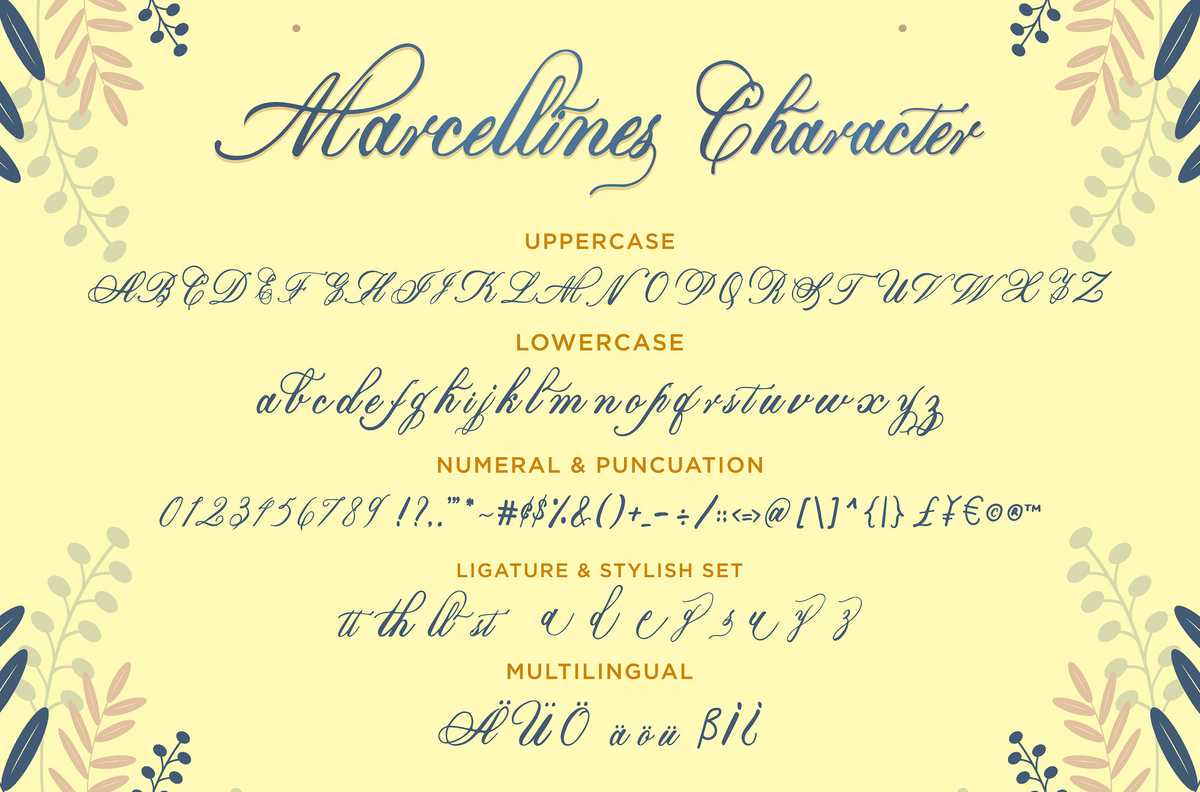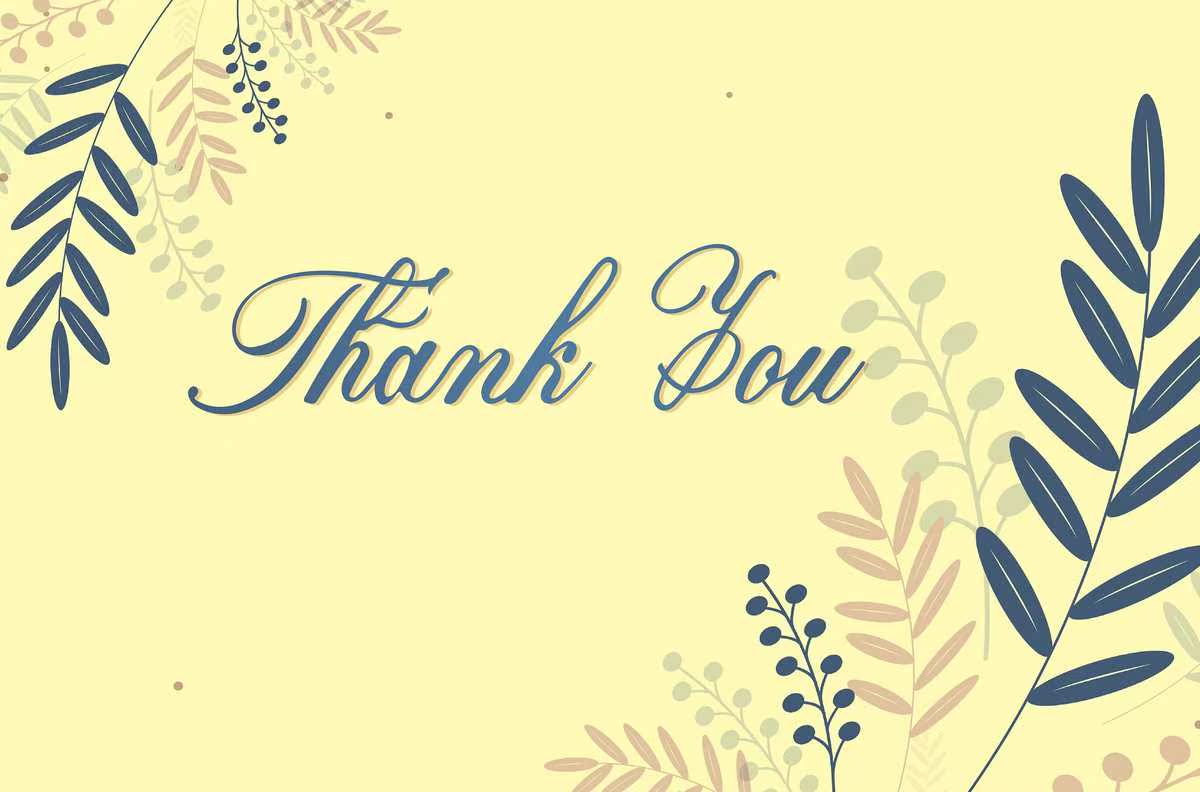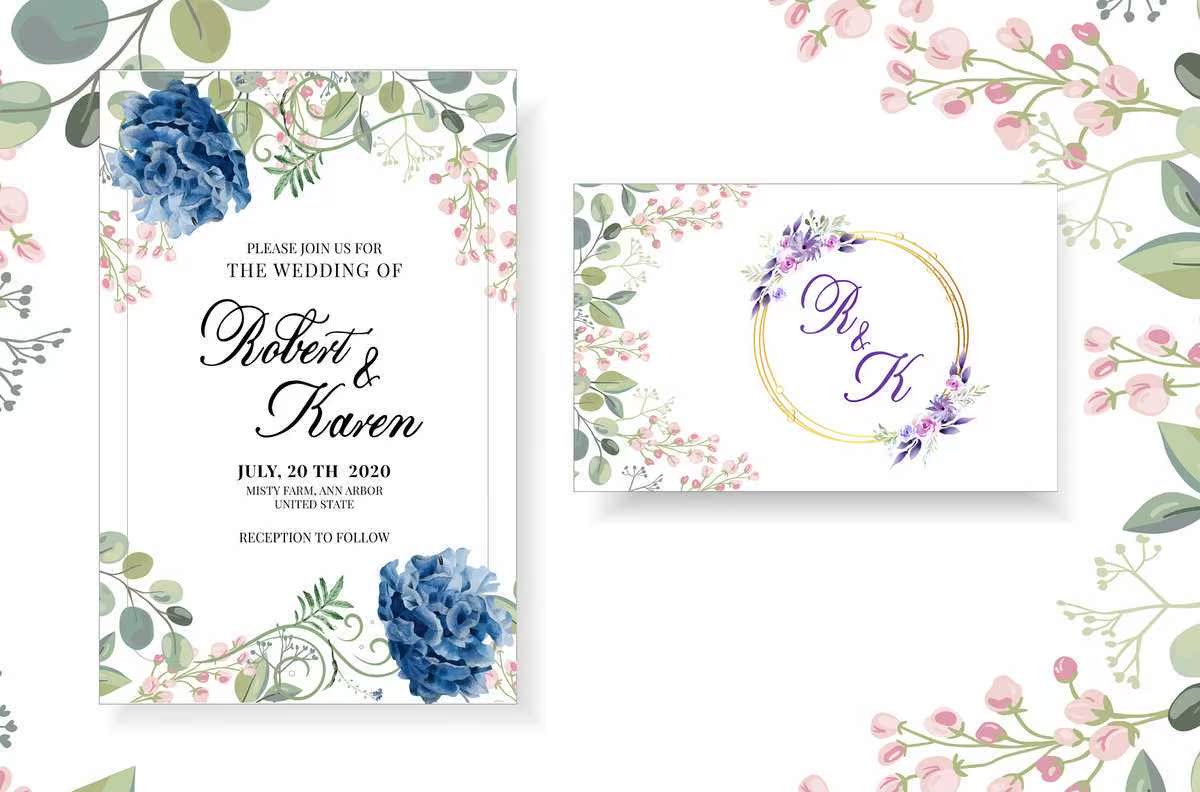
简介马塞利尼是一种现代书法字体。这种字体是直接用毛笔手写的,因此它可以产生具有个性和艺术性的字体。它们非常适合需要标题、标识、服装、邀请、品牌、包装、广告等字体的用户。这种字体有大写、小写、标点符号、符号、数字、样式集,连字等支持多语种。介绍或连字是一种现代书法字体。这种字体是直接用毛笔手写的,因此它可以产生具有特征和艺术性的字体。它们非常适合需要标题、标识、服装、邀请、品牌、包装、广告等字体的用户。这种字体有大写、小写、标点符号、,符号、数字、样式集、连字等支持多语言。